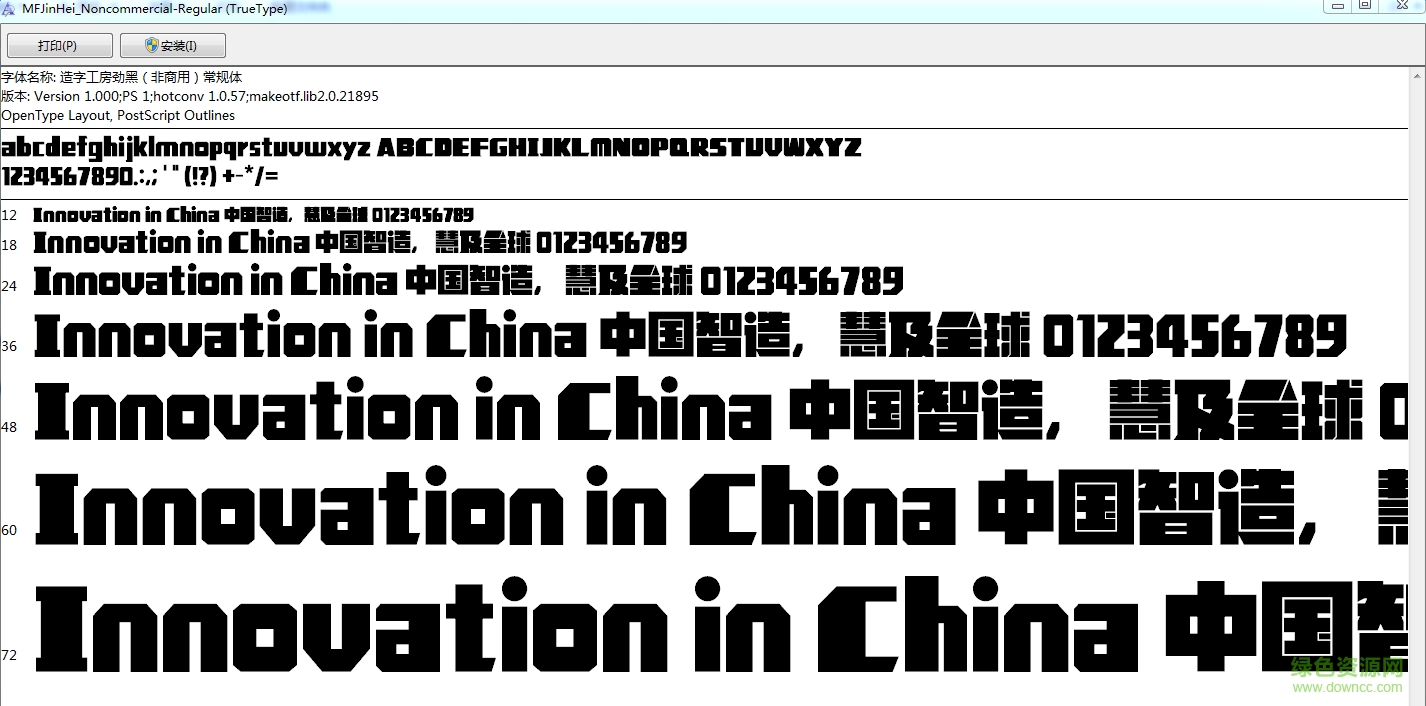
造字工房勁黑字體是一款造字工房類彪悍風(fēng)格字體軟件,勁黑體給人非常粗獷有勁的感覺,適用于大字報(bào)標(biāo)題等廣告宣傳,也深受廣大書法家的喜愛,還有更多好看字體盡情期待,歡迎到綠色資源網(wǎng)下載體驗(yàn)!
造字工房勁黑體筆畫粗厚,字體呈方塊狀,沒(méi)有多余的筆畫,多用做各種廣告字體、宣傳大字報(bào)字體等。